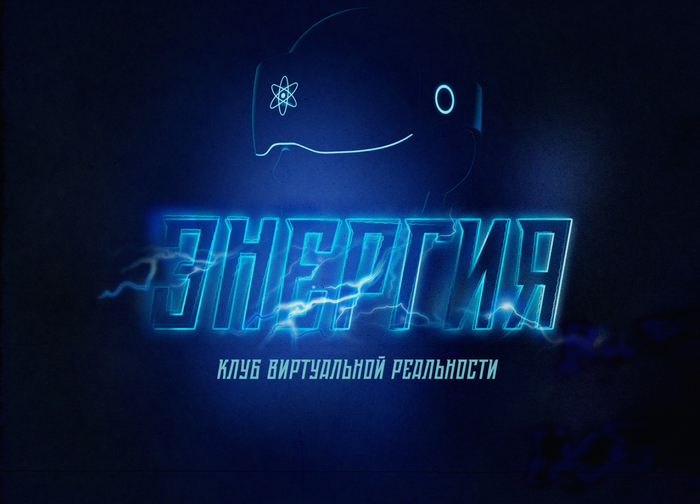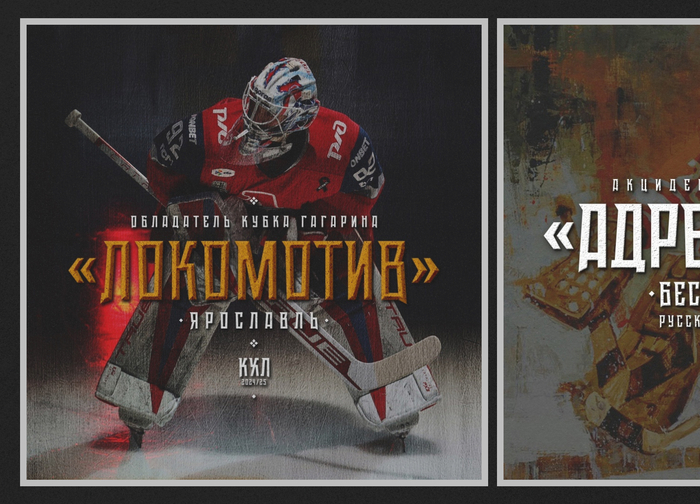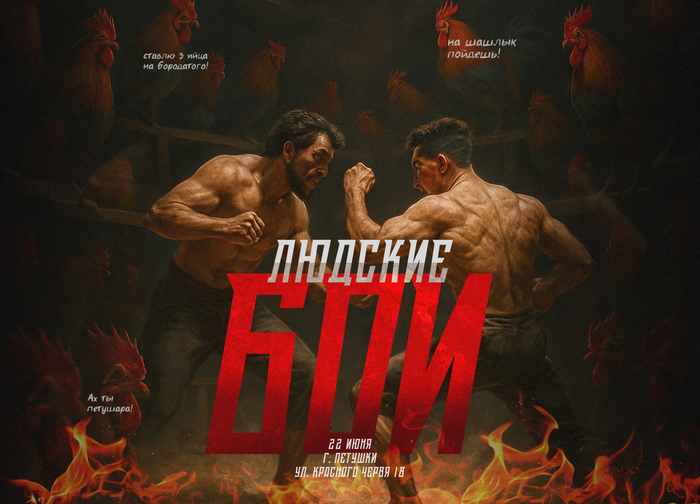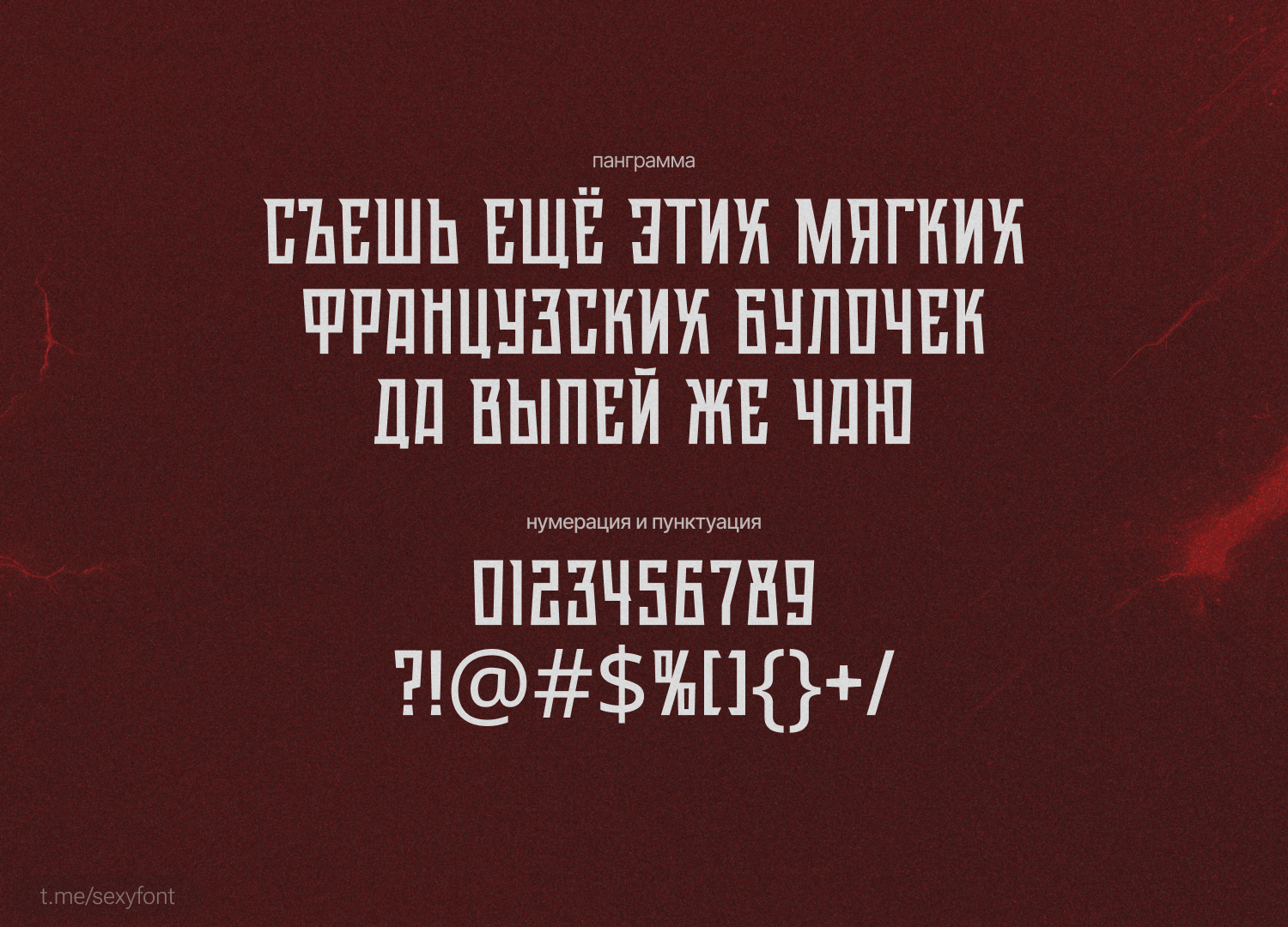
Шрифт Adrenalin
Еще одна презентация крутого шрифта. Брутальный, с острыми формами, но читаемый и внятный. От проверенного автора) Мне шрифт оч. понравился! Особенно наклонное начертание.Автор: Дмитрий Тектов